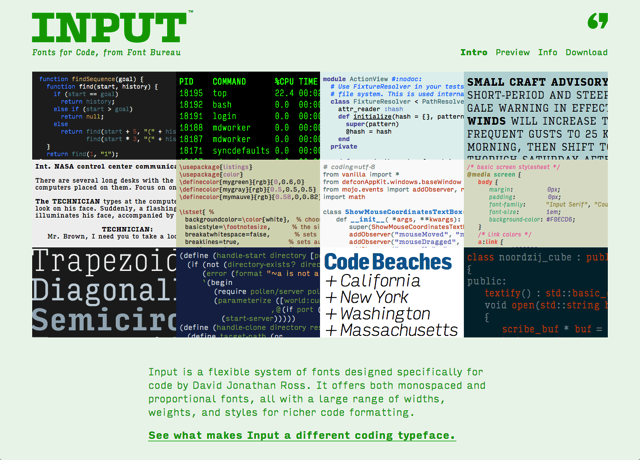
Input Fonts 為編寫程式設計的免費字型組合,更適合長時間大量閱讀
先前我們曾經刊載過一篇「適合程式設計師編寫程式的免費等寬字型整理」專文,獲得不少正面迴響,如同在文章前段所述,工程師在撰寫程式時,通常需要長時間閱讀程式碼,選擇適合閱讀、使用於程式代碼顯示的字型就顯得格外重要。如果你平常也會接觸到程式碼,本文介紹的這款 Input Fonts 可以為你的開發環境提供另一個更適合閱讀的字型選擇。
Input Fonts 網站副標題寫道:Fonts for Code,可以知道它是一款為編寫程式而生的字型組合,由 David Jonathan Ross 等人設計,內建等寬字型(Monospaced Font)和比例字體(Proportional Font),包含各式各樣的字元寬度、字重和樣式設定,透過自訂化調整,讓它更貼近你的閱讀、使用習慣。
其實等寬字型並不適合用於一般文章內文,這是因為所有字元都被固定為相同寬度,但卻已成為撰寫程式時會固定使用的標準字體,當所有字元都能放進相同大小的範圍裡,便能減少排版或閱讀時可能造成的失誤。
然而等寬字型被迫將較窄的字元拉長、把較寬的字元擠壓,大寫字元在小寫字元旁會有受到擠壓的感覺,粗體字元也無法顯示出它的樣貌,會讓撰寫或管理程式碼變得更加混亂。
現今複雜的開發環境正在不停發展、轉變當中,在程式碼排版上應該還能更好,這是 Input 網站裡所提到的字型宗旨,有興趣的朋友不妨參考 Input Fonts Info 詳細說明,就能知道這套字型究竟和其他同類字型有什麼的差異或特色。
比較特別的是 Input Fonts 網站提供「互動式字型預覽」功能,可以直接在網站上調整字型大小、程式碼類型、配色、文字樣式等等,使用者就能知道最適合自己的設定為何,設定好後會即時顯示於網站右邊,當然你也可以點選底下的按鈕來下載該字型組合及設定。